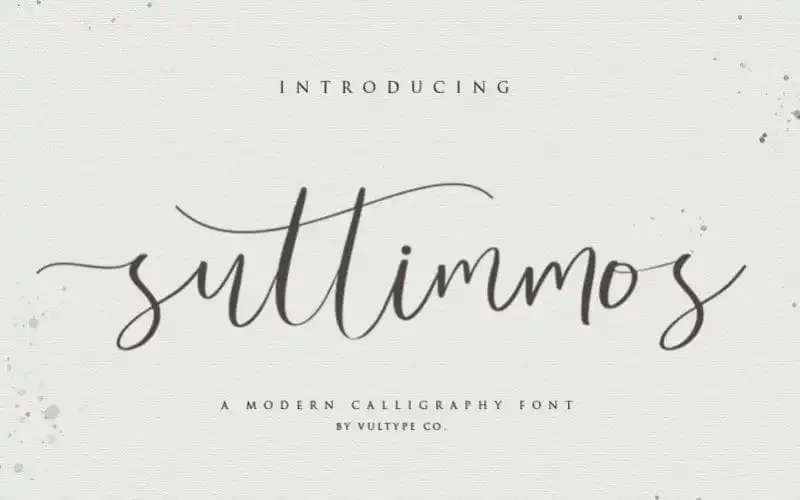
Suttimmos Script Font – Download Grátis
A Suttimmos Script Font é uma elegante fonte script que transmite a sensação refinada de uma escrita calligráfica, mas também tem uma modernidade única. Esta elegante fonte foi criada e compartilhada pelo designer vultype. Ela é um script romântico e moderno, perfeitamente adaptado para aqueles que buscam uma fonte handwritten com estilo boho chic. A Suttimmos Script Font tem um layout de base variável, linhas suaves e formas geométricas incríveis. Além disso, possui alternativas surpreendentes, tornando-a ainda mais versátil e original. Para você que busca estilos únicos e criatividade para seus designs, a Suttimmos Script Font é uma fonte perfeita. Adore o seu estilo único e use-a para criar designs espectaculares!